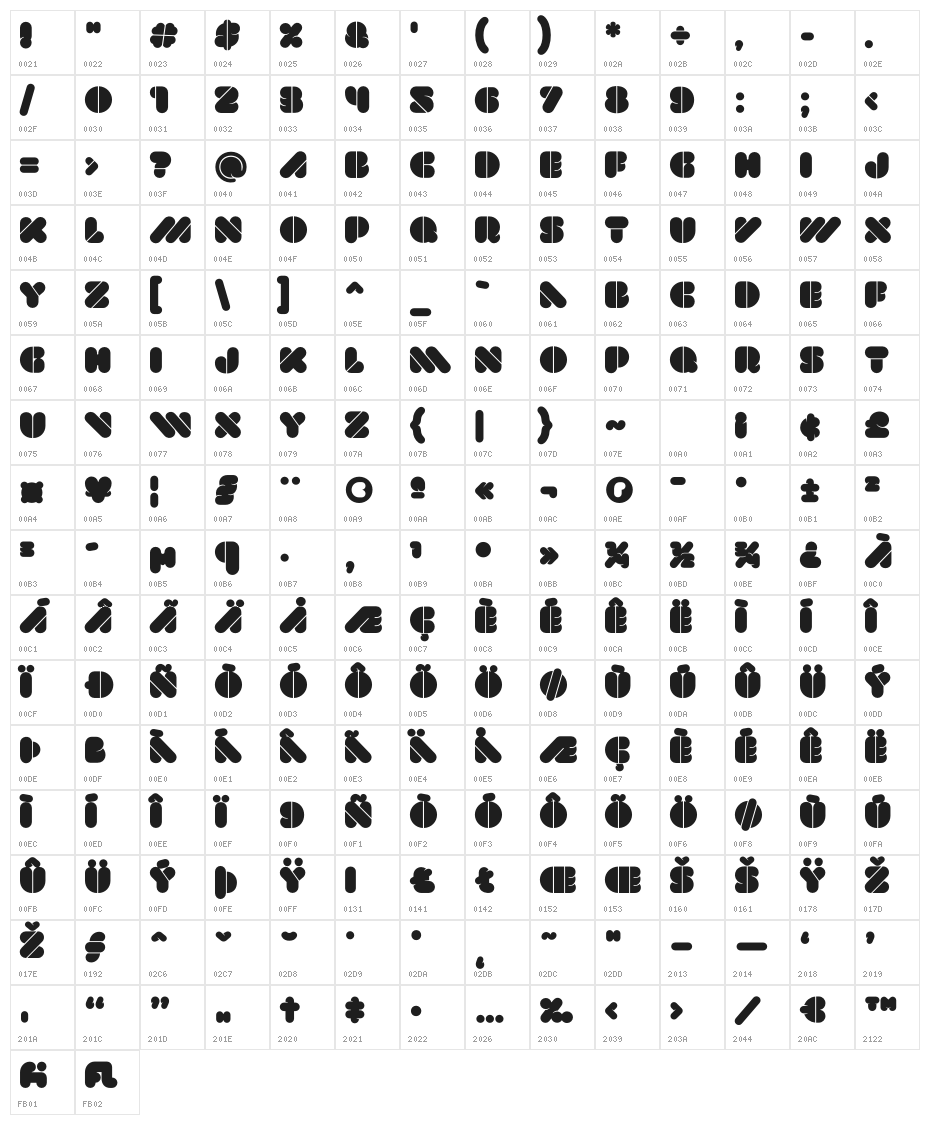
VALStencil Font
✎ Stencil
| Рекомендуемые проекты | Ideal for branding, posters, signage, and any project requiring a modern, industrial aesthetic. |